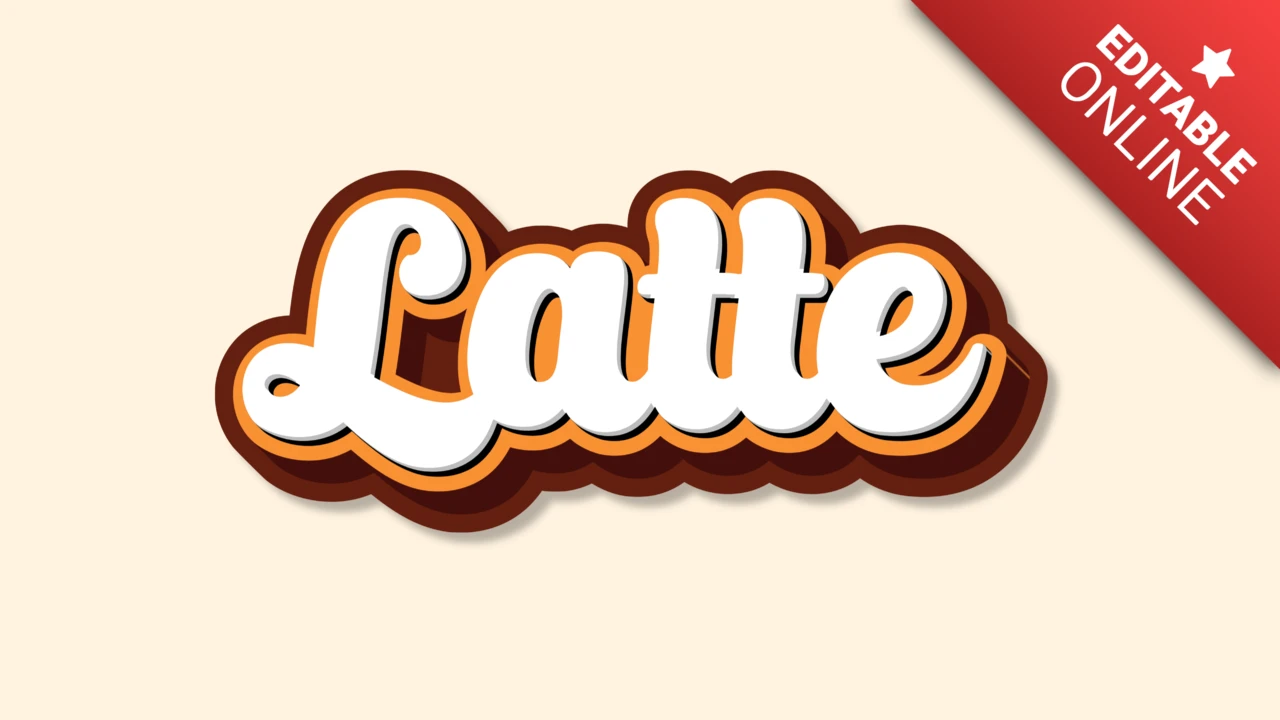
Bruine 3D typografie lettertype
Transformeer je ontwerpen met dit verbluffende 3D-teksteffect, met rijke bruintinten en speelse krommingen die diepte en dimensie toevoegen, perfect voor opvallende graphics en boeiende titels.